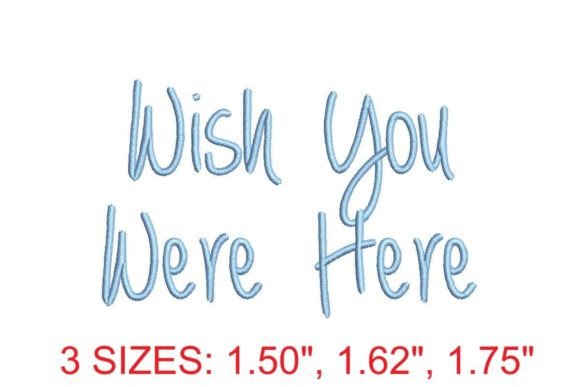
Wish You Were Here Embroidery Font
Doğru tasarım öğelerini bulmak zor olabilir, ancak Wish You Were Here Embroidery Font, çalışmanızı anında bir üst seviyeye taşıyan olağanüstü bir koleksiyon sunar.
İster İsteğe Bağlı Baskı (POD) ürünleri, ister düğün davetiyeleri veya sosyal medya grafikleri oluşturuyor olun, Wish You Were Here Embroidery Font ideal bir uyumdur.